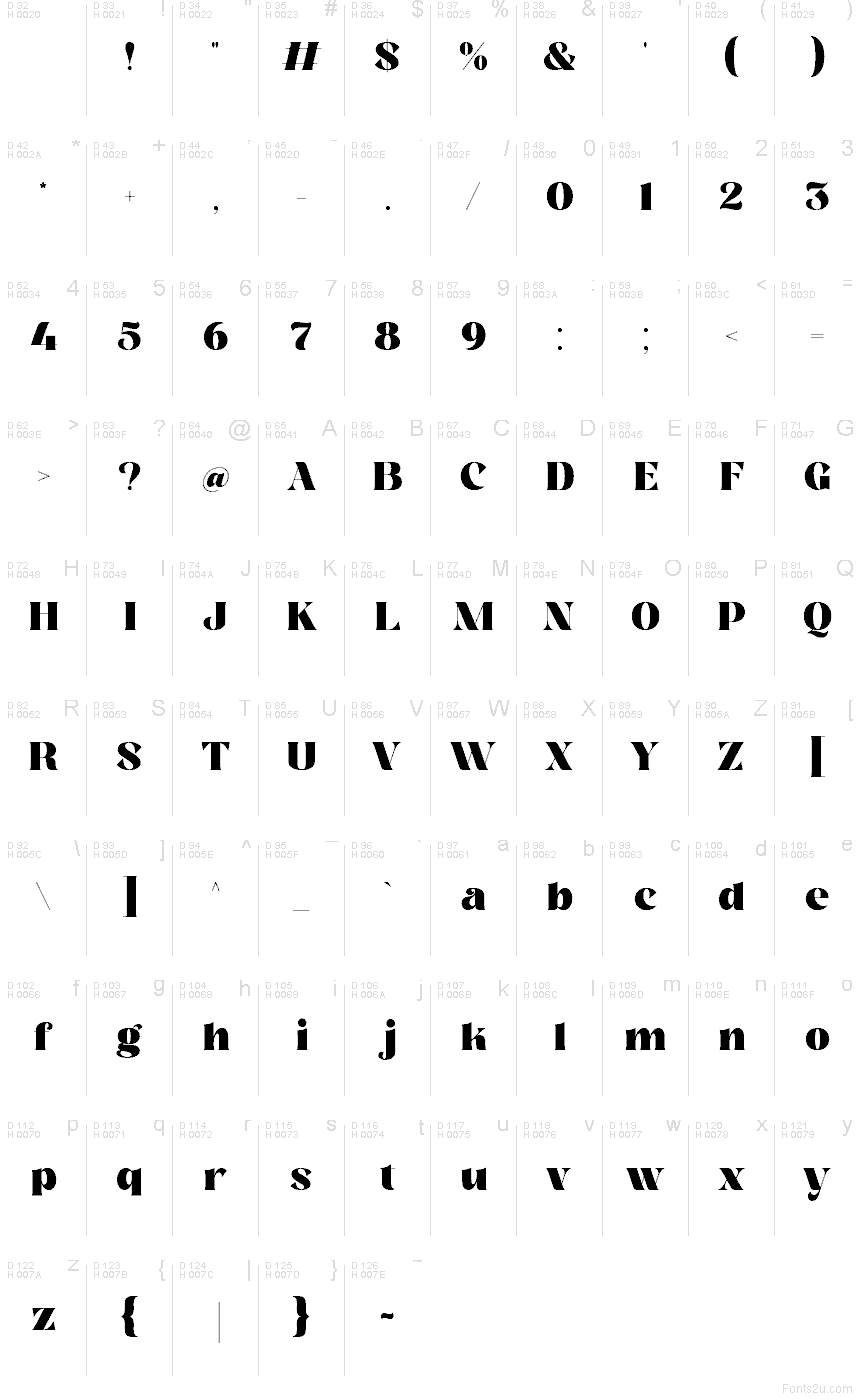
Molra Beauty, realizzata da HansCo, è un font serif gratuito ad alto contrasto, caratterizzato da un'impronta editoriale moderna e legata al mondo della moda. Le lettere uniscono tratti ampi e scultorei a giunzioni sottilissime e terminali appuntiti, dando vita a uno stile elegante, formale e leggermente teatrale, senza mai perdere la sua compostezza.
Si integra perfettamente in testate di riviste, packaging di prodotti beauty, etichette di profumi, inviti per matrimoni e titoli di film, dove gli spazi interni ridotti e le curve sinuose conferiscono un'autentica presenza anche alle scritte brevi. Essendo un font gratuito, è ideale anche per titoli di copertina, brand identity di boutique e iniziali personalizzate, quando cerchi qualcosa di raffinato ma d'impatto.